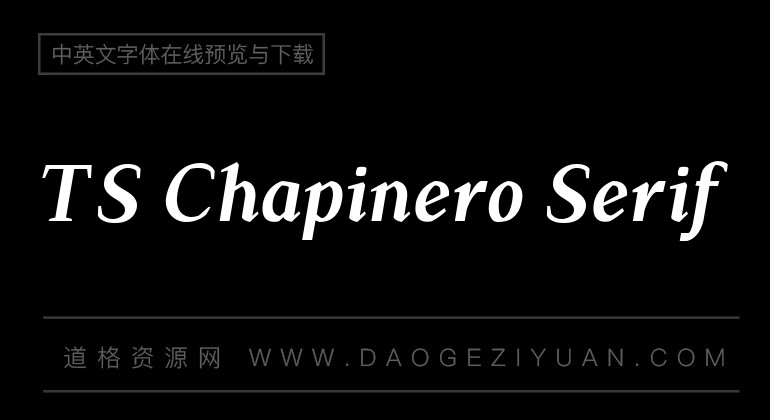
TS Chapinero Serif
? TS Chapinero Serif是一款现代柔和的西班牙衬线字体,由T-26设计师Javier Quintana开发。它具有舒适的曲线,精致的细节和精美的字母,使其成为拥有现代感的经典衬线字体。TS Chapinero Serif拥有8种字重,包括常规,粗体,斜体,粗斜体,细体,细斜体,极细体和极细斜体。它还支持多种字符集,包括拉丁,希腊,西里尔,西班牙,葡萄牙,意大利,波兰,克罗地亚,罗马尼亚,丹麦,瑞典,芬兰,挪威,德国,荷兰,匈牙利,捷克,斯洛伐克,波斯,波斯尼亚,保加利亚,爱沙尼亚,立陶宛,白俄罗斯,乌克兰和克罗地亚。
TS Chapinero Serif是一款非常不错的手写艺术字体,具有很好的视觉感,适合于文化类的宣传设计、商业类品牌的广告和产品包装设计以及个性化文字排版等较多场景。